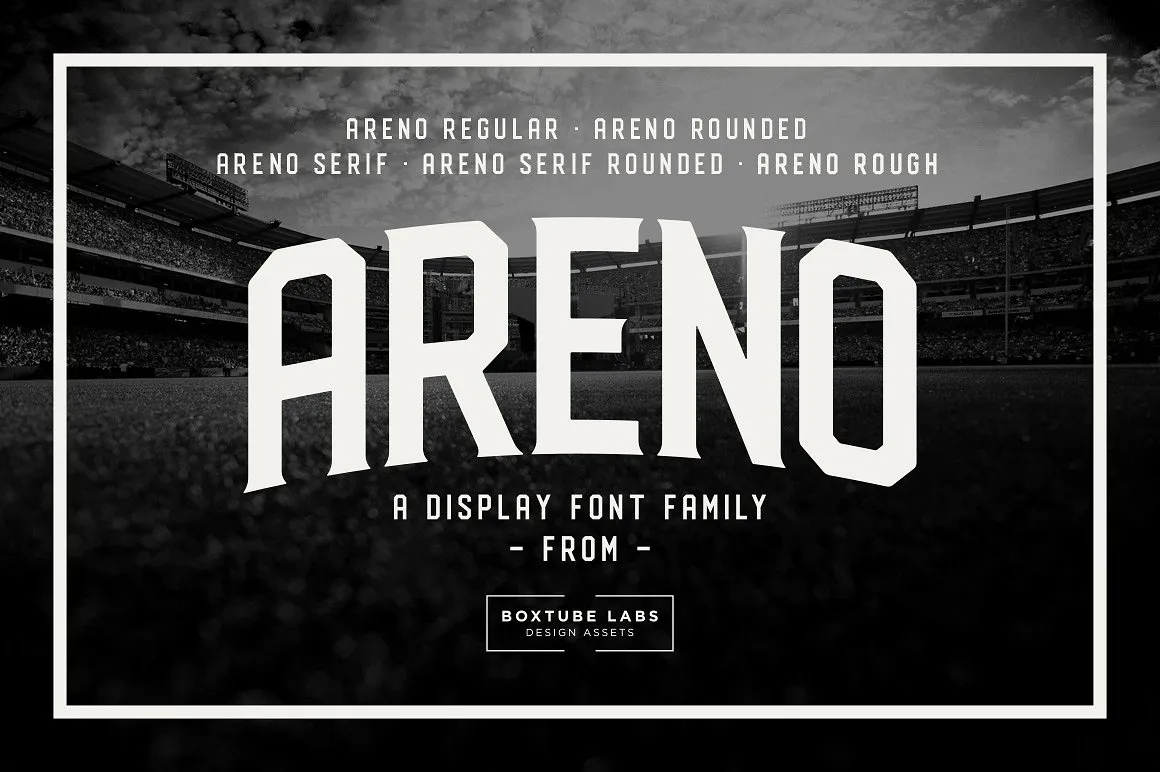
Introduzimos Areno! Esta elegante fonte serif foi criada pelo Designer 178-MC, que pertence à BoxTube Labs. Este é um dos familiares de fontes lançados pela BoxTube Labs recentemente. Areno é uma família de tipografia all caps em estilo serifa com cinco diferentes estilos: Regular, Rounded, Serif, Serif Rounded e Rough. Ideal para a criação de headlines, logos, camisetas e outros designs visuais. Sua linhas ergonômicas e seus detalhes sofisticados dão a ela um aspecto profissional que irá destacar qualquer tipo de design. Com Areno, você pode escolher o estilo adequado para cada projeto – seja para dar um toque mais tradicional em seu trabalho ou criar um design único e criativo. Seja você designer gráfico, editor de imagens ou artista digital, Areno está aqui para ajudar a enriquecer seus projetos.